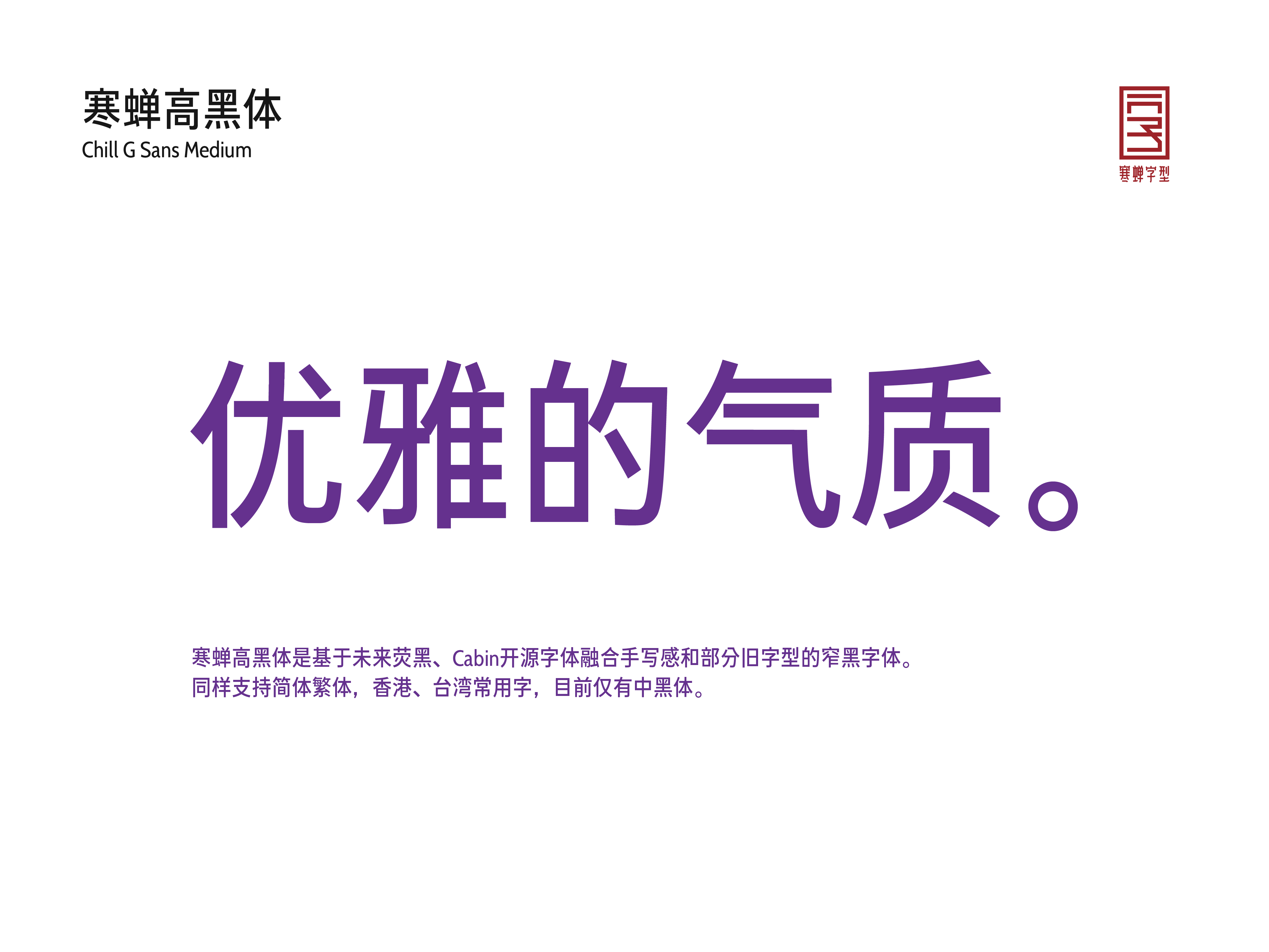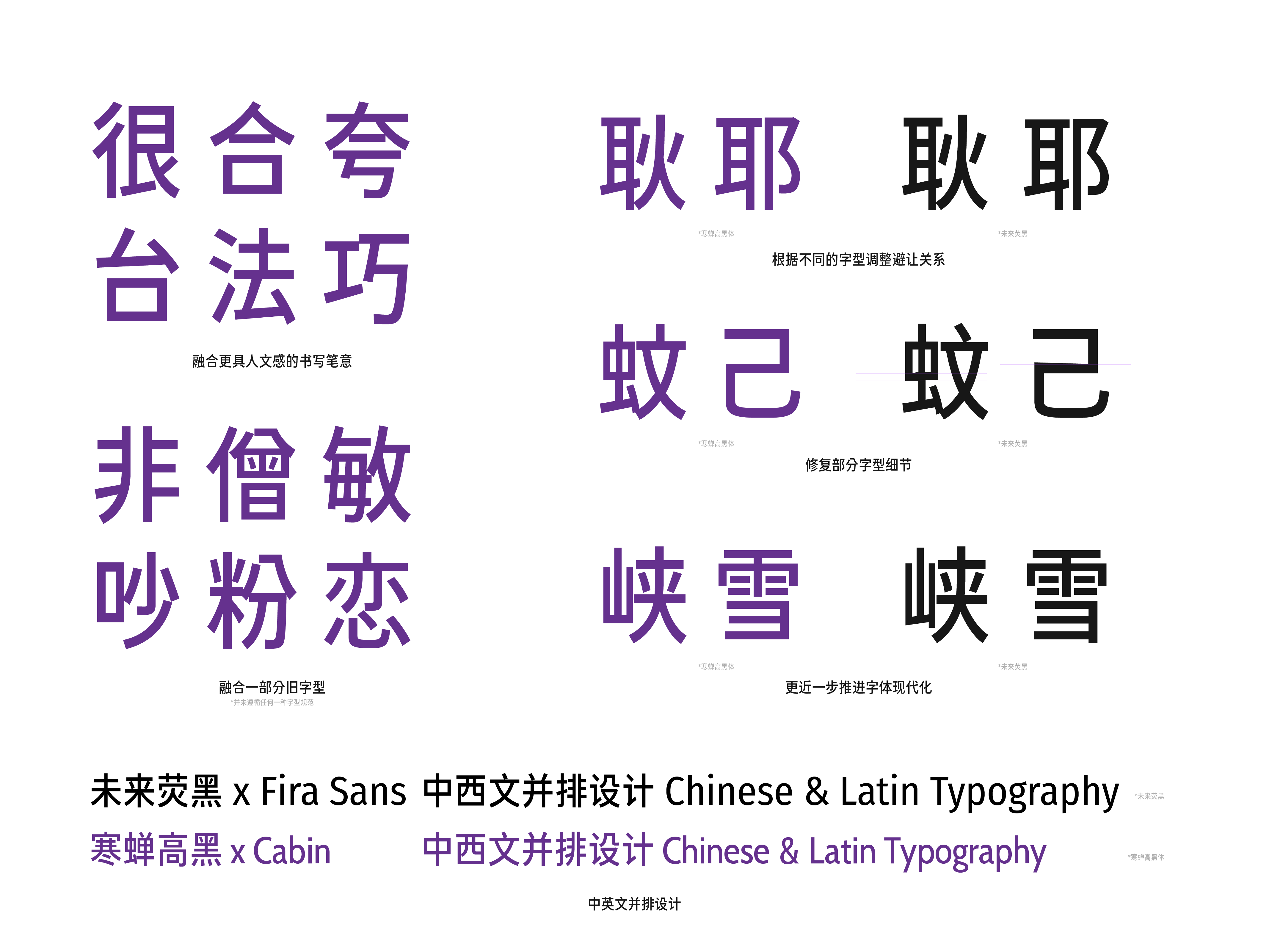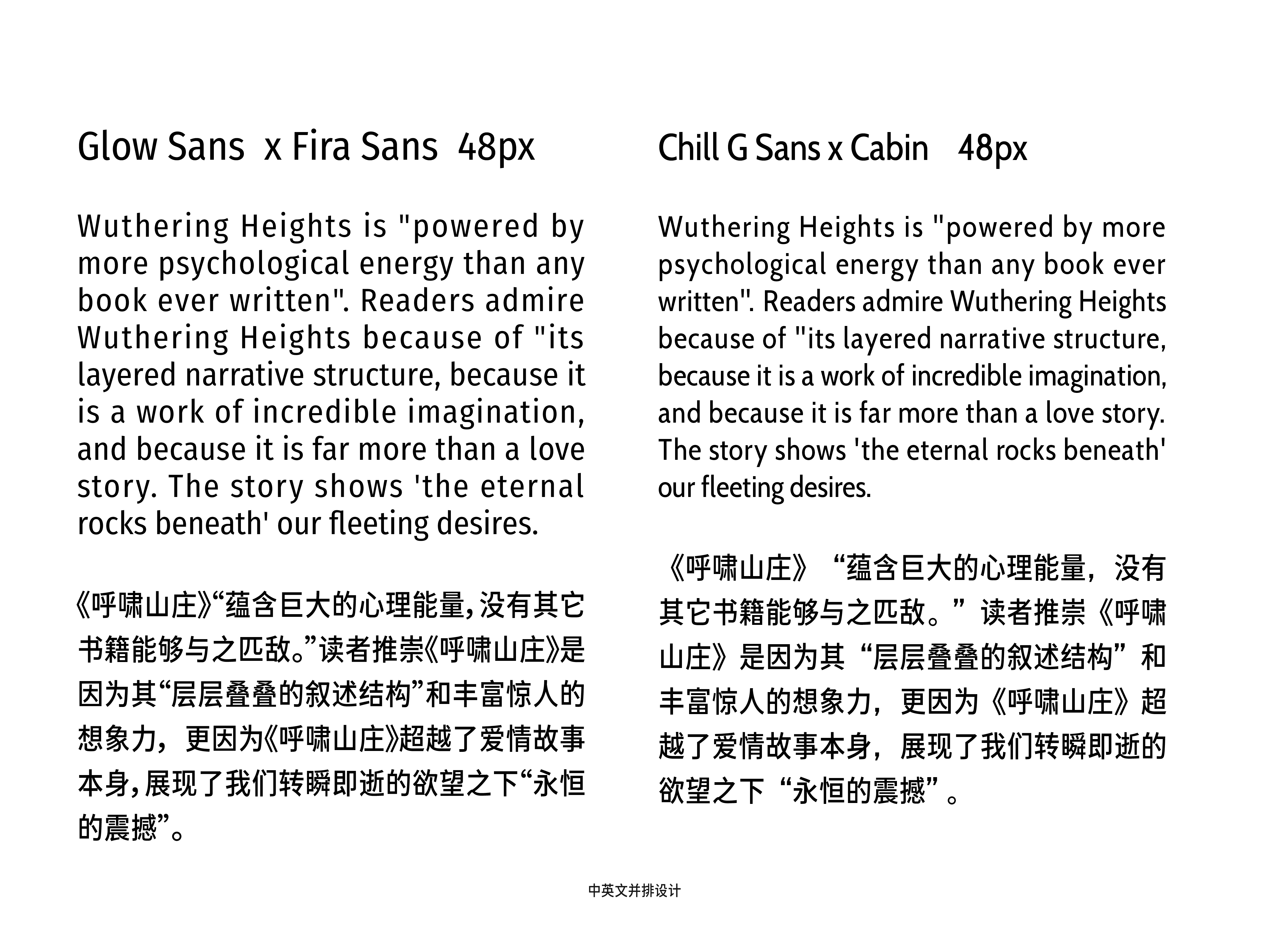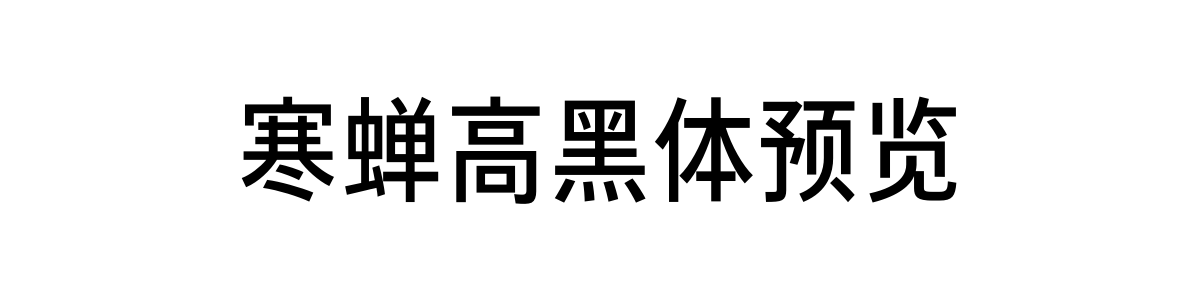
寒蝉高黑体
寒蝉高黑体(Chill G Sans)是一款兼具手写意趣与旧字形质感的现代窄黑体,以未来荧黑的窄黑骨架为基底,同时融合了西文字体 Cabin 的人文主义气质。它在简洁理性的几何结构之上,加入了手写温度与古典字形美感,字形避让关系经过优化,整体干净利落、温润优雅。
团队在开发中手工修正了近 8000 个字符轮廓,字形精度更高,支持简繁中文、港台常用字及日文,西文部分搭配 Cabin 形成统一协调的排版效果。
寒蝉高黑体整体风格优雅、现代、温润又富有人文感。字形修长紧凑,现代感强烈。在未来荧黑平直简洁的笔画基础上,加入了细微的手写笔触,起笔收笔带有柔和弧度,同时吸收了传统印刷老字形的结构特点,既保留了黑体的利落,又不会显得冰冷生硬,气质细腻耐看。